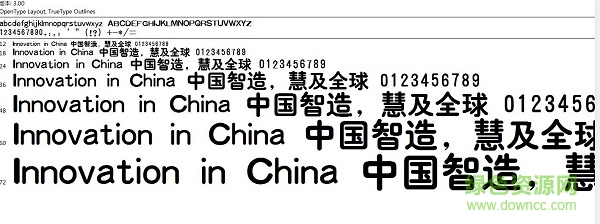
和平粗圓.ttf字體包含了繁體和簡(jiǎn)體兩種,弧度優(yōu)美,粗細(xì)適中,有一種舒展開(kāi)闊的感受,不管是用在正文排版還是包裝設(shè)計(jì)等方面都不錯(cuò),使用的范圍也都非常的廣,歡迎大家在本站免費(fèi)下載!
字面大,起筆處與收筆處為圓形,折筆處呈圓弧狀,筆畫(huà)粗細(xì)適中,適用于女性、兒童和生活用品類(lèi)的宣傳冊(cè)和平面設(shè)計(jì)等